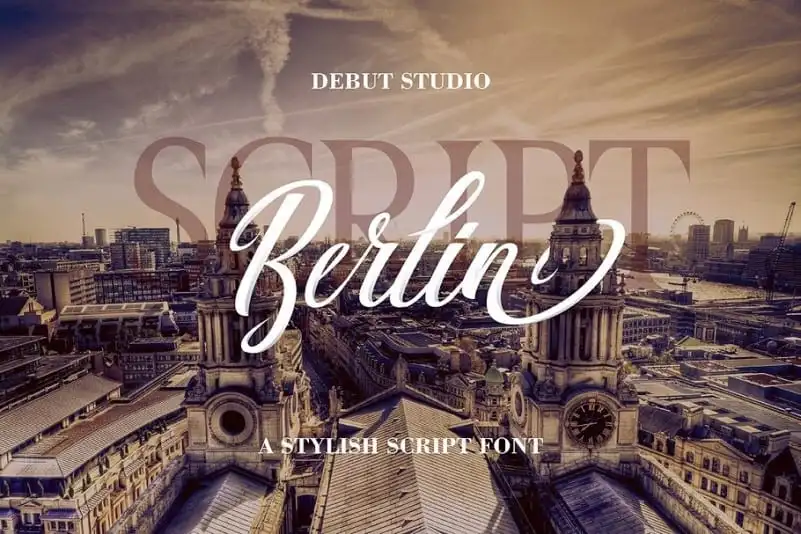
Berlin Script Font
Berlin Script Font é uma nova fonte moderna com influências na calligrafia lançada pela Debut Studio. Ideal para incorporar em qualquer projeto de design, essa fonte se destaca por sua elegância e facilidade de uso, tornando-a perfeita tanto para trabalhos de marca como para decorar. Seu charme sofisticado é especialmente apropriado para aplicações como marcas, assinaturas, fotografias, logotipos, cartões de visita, citações e diversas outras utilizações gráficas. A Berlin Script Font oferece uma leitura fluida e um toque moderno que certamente irá destacar seus projetos, tornando-o uma escolha inteligente para designers buscando estilo único e elegante no seu trabalho.